35 fuentes espeluznantes de Halloween
Una de las mayores oportunidades de marketing año tras año está a solo unas semanas: ¡Halloween! Todo tipo de empresas aprovechan esta temporada organizando sus propias promociones inteligentes de Halloween.
Con el aumento en las ventas durante este período, es realmente una oportunidad de marketing que vale la pena considerar. Es probable que una gran parte de cualquier trabajo de diseño para este tipo de publicidad requiera una buena cantidad de texto. Esto significa que debe elegir las mejores fuentes de Halloween para transmitir de manera efectiva su mensaje espeluznante.
Las mejores fuentes de Halloween
Cada año, parece que hay un brote de zombis para los nuevos tipos de letra de Halloween. Esto no es sorprendente, ya que hay una gran demanda de carteles, volantes y boletos de Halloween para llamar la atención de los consumidores potenciales.
Las tipografías típicas de esta temporada muestran letras que rezuman sangre, suciedad o jugo de chatarra. Pero si desea atraer a más clientes, no es malo elegir algo nuevo para sus diseños con temática de terror. Hay muchas fuentes frescas de temporada que puedes usar para el póster de diseño espeluznante en el que estás trabajando.
Dos de los mejores para esta temporada son:
- La fuente Zombie
Los zombis son una gran cosa en este momento, gracias al exitoso programa de televisión 'The Walking Dead'. Si está planeando una promoción o un anuncio con temática de zombis, puede replicar la fuente utilizada por el programa para un reconocimiento instantáneo.
Es cierto que el tipo de letra no se parece a la típica fuente espeluznante con exudado y goteos, pero es algo nuevo pero reconocido mundialmente. Esto puede atraer fácilmente a más clientes, especialmente a aquellos que aman el programa.
De lo contrario, inspírate en las clásicas películas de serie B de zombies de los años 60 y 70 para elevar el 'ambiente' zombi de tu diseño.
- La fuente inspirada en Harry Potter
Si desea una fuente más sutil pero aún espeluznante para su póster de Halloween, elija entre la variedad de Harry Potter -tipografías inspiradas.
La mayoría presenta una característica clara y legible a pesar de sus tonos espeluznantes. Las fuentes inspiradas en HP son una excelente fuente de copia para invitaciones de Halloween, folletos personalizados y carteles especiales. También son bastante versátiles, ya que tanto los niños como los adultos pueden reconocer las fuentes de la famosa franquicia de libros y películas.
Además, el uso de una fuente inspirada en HP agrega un toque instantáneo de misterio, caos y magia a su diseño.
Las fuentes inspiradas en Zombie y HP son solo dos ejemplos de grandes tipos de letra de Halloween. Para obtener más opciones, aquí hay 35 fuentes espeluznantes de Halloween que puede usar para sus promociones anuales.
Monsterific BB de Blambot
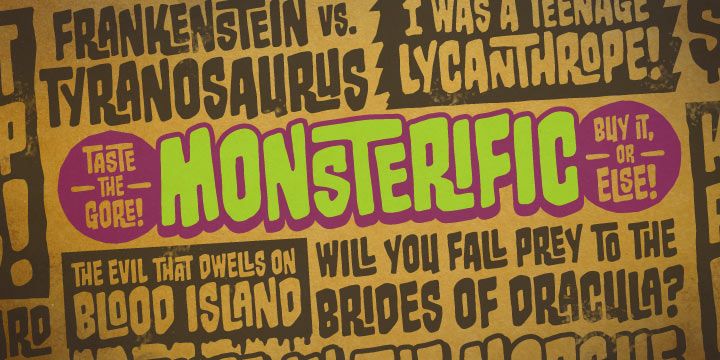
Monsterific BB se inspiró en los títulos clásicos de las revistas de terror de los 70 y cuenta con un gran complemento de personajes europeos y más de 160 Autoligatures de Opentype. ¡Perfecto para Halloween o cualquier época espeluznante del año!
Anochecer por tipo verde
Ático YWFT de YouWorkForThem
Este majestuoso ático de YWFT está lleno de sorpresas, con magníficas alternativas estilísticas y características sofisticadas que incluso Scooby Doo podría saltar en tus brazos, si no fuera por tus niños entrometidos.
WILD2 Ghixm por Fontry West
Ghixm es una retrospectiva de los cómics de terror y los carteles de películas de las décadas de 1960 y 1970. Sus formas fluidas recuerdan a tumbas acuosas y horrores innombrables con tentáculos. Estas formas retorcidas recuerdan a los títulos que harán que se te erice la piel. Ya está deformado y retorcido, así que no dudes en abusar de él. Este rostro puede tomarlo y aun así transmitir su mensaje caótico.
Eso es asqueroso
Esta fuente fue solo por diversión. Tiene solo 26 caracteres en mayúscula. Sin puntuación, sin minúsculas, sin números. Lo hice estrictamente por diversión.
Mantícora
Una fuente de pincel / marcador en negrita en mayúsculas. Incluye números, puntuación, un par de glifos adicionales y alternativas para algunas letras. Encontré la fuente ideal para estampados al estilo de los 80, material de temática de terror o cualquier gráfico de temática punk / grunge / urbana.
Lord Zero de Set Sail Studios
Echa un vistazo a nuestra fuente más ruidosa y salvaje: ¡Lord Zero! Esta fuente hecha a mano es perfecta para captar la atención de sus carteles, logotipos, ropa, ilustraciones de álbumes o cualquier diseño que necesite un buen toque de proverbial.
Temiendo
Veritus es una fuente de pincel con personajes malvados. Incluye letras mayúsculas en inglés, números y puntuación simple. Algunas letras también tienen versiones alternativas que puede alternar con el bloqueo de mayúsculas.
Dolor sin fin
Endless Sorrow es una fuente de visualización versátil en mayúsculas inspirada en la tipografía vintage que generalmente se muestra en carteles, libros y CD Cover . La altura irregular de la fuente representa claramente la sensación de dibujado a mano y humanis. Puede usarlo para sus próximos proyectos artesanales: póster, volante, pancarta, ilustración, portada, etc.
Bestia de Tugcu Design Co.
Beast es una fuente de pincel con letras mayúsculas, letras alternas, números y puntuación. Algunas letras tienen versiones alternativas que puede alternar con el bloqueo de mayúsculas.
Fiesta de monstruos
Monster Party es una pantalla ilustrada con mucho carácter para cualquier ocasión inquietante. Viene en dos estilos, Monsters y Bones para lo que requiera tu situación.
Muertos Typeface
Muertos es un tipo de letra extraño con letras mayúsculas multilingües, letras alternas, números, puntuación y adornos.
Deathgrin de Set Sail Studios
Deathgrin es una fuente de visualización de estilo terrorífico hecha a mano, garantizada para darle a tu texto una buena dosis de terror. La fuente es solo en mayúsculas, sin embargo, incluye algunas alternativas y puntuación básica.
Myster de Dzianis Serabrakou
Myster es una fuente verdaderamente aleatoria: cada letra minúscula tiene tres alternativas, que se intercambian en el conjunto. Esto hace que Myster parezca vivo, hecho a mano, pintado para una ocasión especial, en lugar de una fuente seleccionada de una caja de tipo normal ...
Por supuesto, el carácter místico de la fuente define el alcance de su uso: industrias cinematográficas, de juegos y editoriales. Sin embargo, el campo de aplicación de Myster va más allá de ellos. Esta fuente es capaz de crear la atmósfera deseada en envases, libros infantiles, revistas, así como en publicidad.
Losa inestable por una nueva máquina
Unstable Slab es la versión slab serif de nuestra fuente Unstable. Cuenta con una línea de base variable para darle un aspecto inestable, y las mayúsculas y minúsculas difieren ligeramente y se pueden mezclar para lograr un aspecto menos uniforme.
Creepster Pro de Sideshow
¡Es espantoso! ¡Es sangriento! ¡Es horriblemente alegre! Es Creepster Pro, la nueva fuente espeluznante de Squid y Sideshow. Esta fuente llena de miedo tiene tantas alternativas que es como coser tu propio monstruo cada vez que la usas. Creepster Pro: ¡Perfecto para todas sus espeluznantes necesidades gráficas!
Zona muerta por TypeArt Foundry
Monster Fiesta
Un tipo de letra serif poco convencional, divertido y espantoso inspirado en el clásico animagico de Rankin Bass de 1969 titulado Mad Monster Party.
Horror de La Boite Graphique
El terror es, como su nombre indica, una tipografía expresiva tremendamente genial para ilustrar temas como: atmósfera de noctura, terror, película de zombies, hard rock, festival, halloween… Acompañado de muchos adornos puedes ilustrar fácilmente estos temas.
Martyric por Aring Typeface
Tipografía de estilo basura salvaje.
Smashing de PintassilgoPrints
Smashing es un tipo de letra robusto, con un toque diferente. Es una fuente masiva en mayúsculas con glifos que rebotan, positivamente en negrita pero bastante de buen humor. Sus ranuras para mayúsculas y minúsculas almacenan diferentes formas de letras, lo que brinda opciones prácticas para elegir.
Schwarz de Miguel Ibarra Design
Schwarz es un tipo de letra Black Letter inspirado en todo lo que es negro. Los bordes irregulares y las diagonales afiladas hacen de Schwarz una fuente que golpea la cabeza. También se encuentran disponibles algunas ligaduras y alternativas estilísticas.
Fluffy Slacks BTN rompiendo la norma
Fluffy Slacks es un tipo de letra vestido informalmente perfecto para aplicaciones informales de señalización, titulares y visualización.
Cabeza encogida BB de Blambot
Shrunken head es una fuente de título de cómic clásica y angustiada. La familia consta de cursiva regular, cursiva clara y cursiva clara.
Ewing Julian - Tipo de letra en capas
Ewing Julian es una tipografía 100% artesanal. Con 5 estilos que se complementan entre sí, te dan un diseño de terror profesional. Alfabeto completo en minúsculas y mayúsculas con algunos signos de puntuación y símbolos. También un paquete gráfico adicional para hacer que su diseño sea aún más impresionante.
Manicuore de PintassilgoPrints
Manicuore es un tipo de letra dibujado a mano inspirado en carteles de películas italianas por el prolífico cartel de la película artista Symeoni (también conocido como Sandro Simeoni). Siendo un pintor, retratista e ilustrador talentoso y hábil, Symeoni disfrutó de una carrera larga y fructífera y fue notablemente productivo durante los años sesenta y setenta.
Beats
Wolfsblood de Monotype
Wolfsblood es una nueva imagen de Jim Ford, adaptada de logotipos escritos a mano por bandas de punk rock como The Misfits y Bad Brains. El estilo se remonta a Hollywood y la explosión de películas de ciencia ficción, terror y explotación de bajo presupuesto, que también tuvieron una influencia en el punk rock.
Frontline por TypeArt Foundry
Titulador emocionante para grado B cartel de la película .
Hammerhead de TypeArt Foundry
Cepillo artístico
68 significado
Artsy Brush se inspiró en el pincel dibujado a mano de ink & tints para crear un desorden natural que podría ayudar a una buena visualización, usos para etiquetado, ropa, pantalla de cine, logotipo de banda, título de película, conciertos o álbum de portada.
Sinister Black de Skyhaven Fonts
Pincel de historia
Story Brush es la fuente de pincel de alto nivel de detalle que tiene más de 240 glifos. Viene con 2 Verison Reguler e inclinado. Esta fuente está equipada con la función OpenType para personalizar su diseño. Esta fuente está diseñada para diseño de camisetas, logotipos, diseño de terror, grunge, etc.
Rag FY de Fontyou
Rag FY, una tipografía salvaje y dinámica, con dingbats de animales locos. Perfecto para titulares, carteles, textos breves o diseño de logo .
Cepillo Dexsar
Dexsar Brush es la fuente de pincel de alto nivel de detalle que tiene más de 240 glifos y está equipada con la función OpenType para personalizar su diseño. Esta fuente está diseñada para fines de diseño, como camisetas, logotipos, carteles, etc.